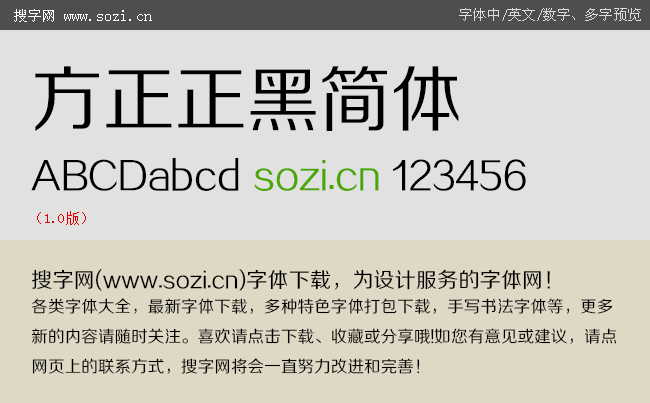
方正正黑簡體
搜字網(wǎng)提供一款方正正黑簡體中文藝術(shù)字體下載,正黑體取傳統(tǒng)黑體結(jié)構(gòu),筆形全部采用平行、垂直與弧度的流線形設(shè)計(jì),簡潔易識(shí)、美觀大方,具有個(gè)性,加之鏡像對(duì)稱的現(xiàn)代構(gòu)成形式,達(dá)到莊重與簡潔有機(jī)融合、設(shè)計(jì)感與閱讀功能兼?zhèn)涞淖罱K效果。適合書籍排版,報(bào)紙排版,海報(bào)設(shè)計(jì),包裝設(shè)計(jì)等廣告設(shè)計(jì)場(chǎng)合應(yīng)用。